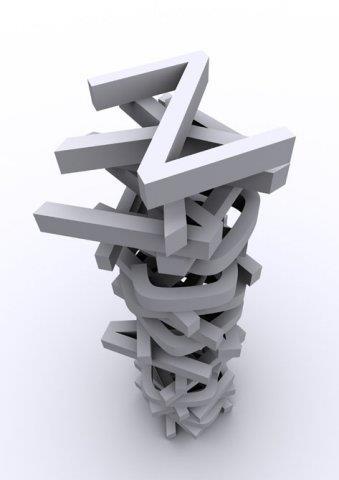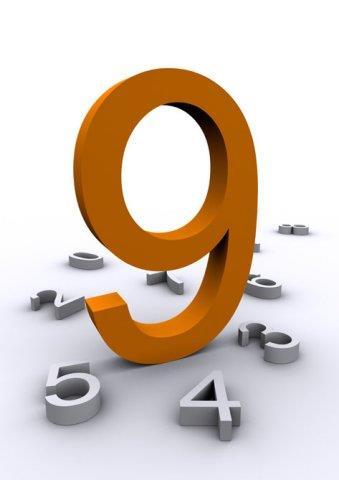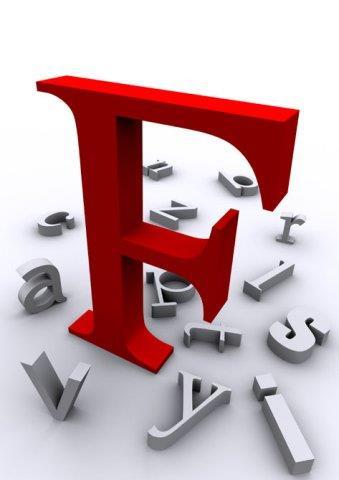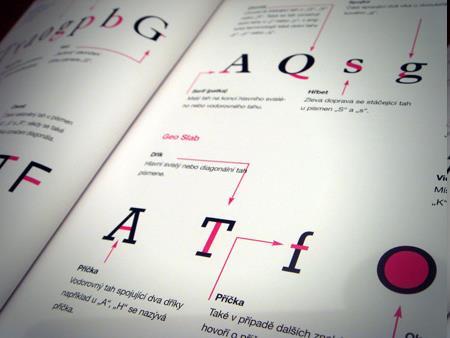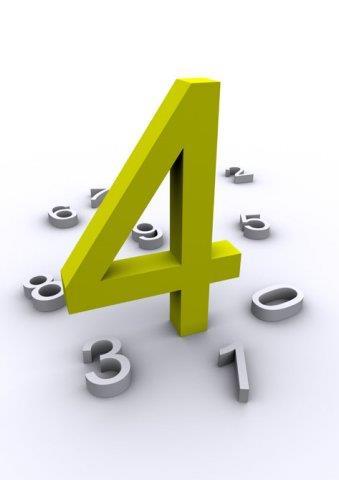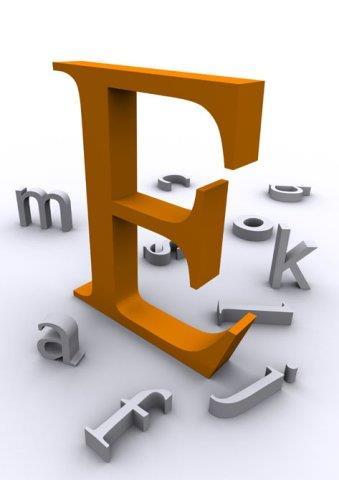
Počítačová typografie
1 Počítačová typografie
2 Typografie je nauka o tom, jak má tiskovina vypadat. Proč se o typografii učíme? Každý z nás běžně připravuje nějakou tiskovinu a požadavky na její kvalitu a zpracování jsou všude na světě jednotné. Měla by být: dobře čitelná esteticky působící přehledná Úvod
3 Úvod typografická pravidla by měl znát každý, kdo se pouští do tvorby tiskovin Slovo TYPOGRAFIE se skládá ze dvou významů typus = znak, vzor grafó = píši
4 Typy písem patková (serifová) tahy písmen zakončeny patkami mají obvykle stínování bezpatková (grotesková) patky chybí tahy stejně silné, slabé stínování málo zdobená kaligrafická a volně psaná vychází z kaligrafických skriptů písem psaných rukou dekorativní písma plakáty, reklamy, oznámení
5 Velikost písma skutečná velikost písma závisí na typu písma udává se v bodech volí se podle formátu a typu tiskoviny dětská knížka bodů text text učebnice, knihy většího formátu bodů text text beletrie pro dospělé 10 bodů text text časopisy 9 bodů text text noviny 8 bodů text text
6 Řezy písma varianty písma, mající společnou osnovu (výškové proporce) a základní kresebné znaky řezy písma slabé light obyčejné regular polotučné bold tučné heavy extratučné black sklon stojaté normal kursivní italics šířka písma zúžená condensed normální rozšířená expanded
7 Doporučení pro používání písma Typ a řez nepoužívej v dokumentu více než 3 typy písma pokud jsou z různých skupin, musí se výrazně lišit Velikost nepoužívej více než 3 velikosti jednoho písma zřetelně odlišené Čím delší text, tím čitelnější písmo používej jednoduchá patková písma jejich výhodou je, že se dá dobře sledovat řádek bezpatková písma jsou lépe čitelná za šera (letáky, titulky, nadpisy)
8 Odstavec základní stavební kámen textu každý blok textu se ukončuje stiskem klávesy Enter odstavcová zarážka posunutí prvního řádku v odstavci v celém textu stejné vlastnosti odstavce pozice levého a pravého okraje odsazení prvního řádku mezera před a za odstavcem řádkování zarovnání tabelátory vzhled a chování odstavce
9 Odstavec psaní textu do odstavce zalamování řádků automatické dělení slov nucené zalomení Shift+Enter zarovnání odstavce doleva na střed plakáty, pozvánky doprava ojediněle do bloku rozšiřování mezer mezi slovy zhoršuje čitelnost textu pozor na krátké odstavce
10 Mezery mezi písmeny, mezi slovy mezi písmeny p r o s t r k á n í zvýrazňují text mezi slovy automatické pevná (nedělitelná) mezera na místě kde nesmí dojít k zalomení řádku Ctrl+Shift+mezerník
11 Základy psaní textu - interpunkce tečka, čárka, dvojtečka, středník, otazník, vykřičník těsně za slovo bez mezery a za ní mezera dvojtečka u sportovního výsledku bez mezery tečka za nadpisem se nepíše
12 Základy psaní textu - znaménka uvozovky těsně ke slovu bez mezer závorky () těsně ke slovu vně mezera spojovník - je na klávesnici spojování slov př. česko-anglický pomlčka je delší oddělovač větných celků mezery před i za nahrazuje spojovník automaticky
13 Základy psaní textu - znaménka matematická znaménka + - = píší se s mezerami výpustek nejsou to tři tečky, ale jeden znak Alt apostrof těsně ke slovu Alt
14 Základy psaní textu psaní čísel věta nesmí začínat číslicí v textu vyjadřujeme čísla slovy mimo datum, letopočet rozdělení po třímístných skupinách pevná mezera násobky bez mezer 10krát datum s tečkami a mezerami označení měn a fyzik. jednotek oddělujeme pevnou mezerou
15 Základy psaní textu zkratky ne na začátku věty vyznačovaní kurzivou tučnou kurzivou p r o s t r k á n í m jiným písmem podtržené písmo nepoužívat Dokážeš najít zpětně v prezentaci moje prohřešky proti pravidlům typografie, o kterých jsme právě mluvili?